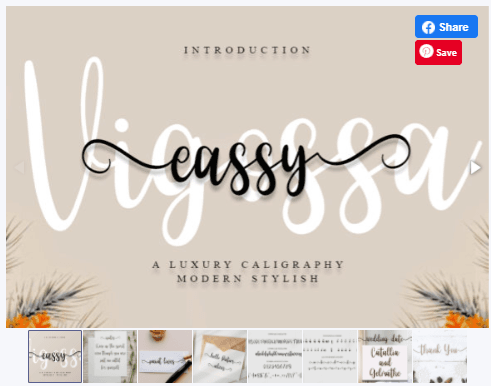
Eassy Vigossa Font
Eassy Vigossa - превосходный рукописный шрифт. Его можно использовать для различных целей, таких как логотипы, свадебные приглашения, заголовки, футболки и многое другое. Этот шрифт имеет кодировку PUA, что означает, что вы можете легко получить доступ ко всем глифам и росчеркам!